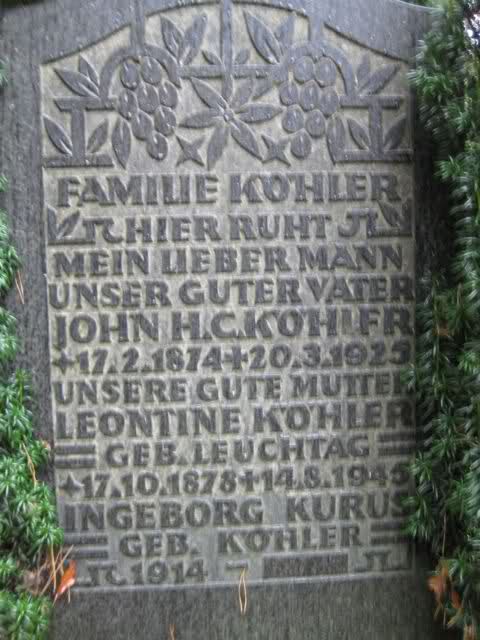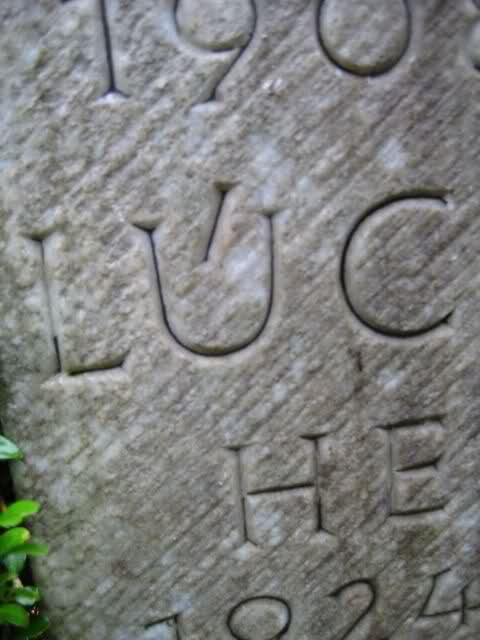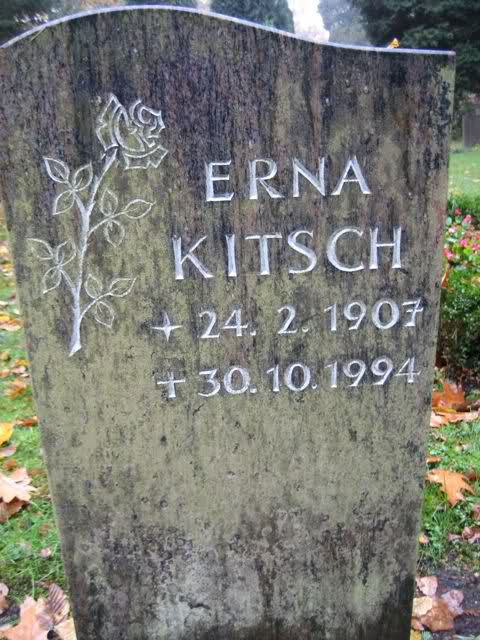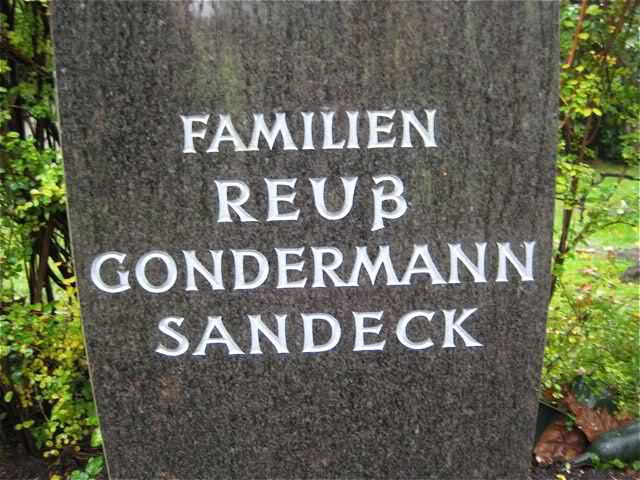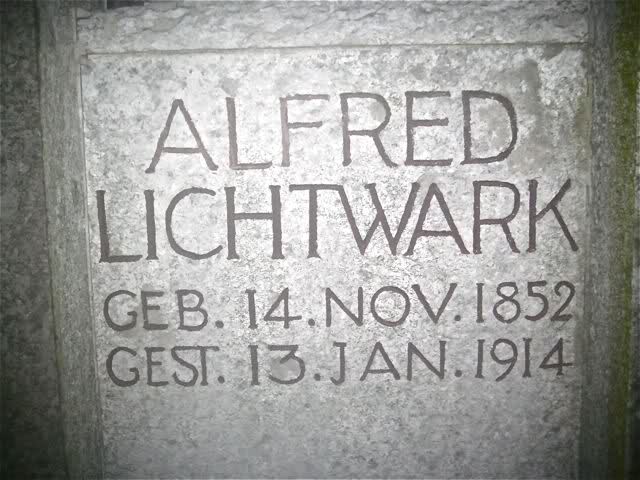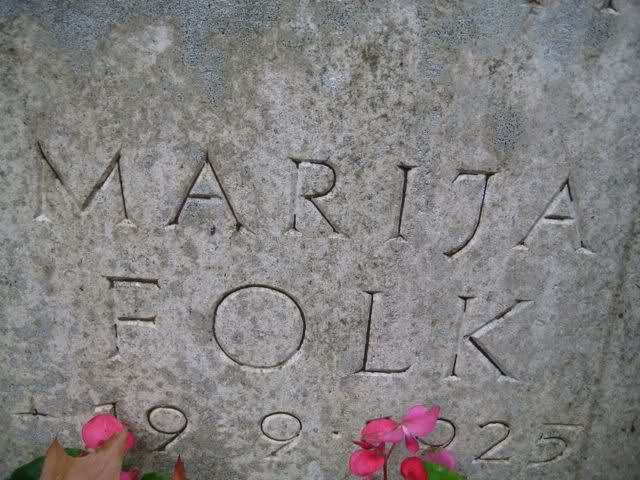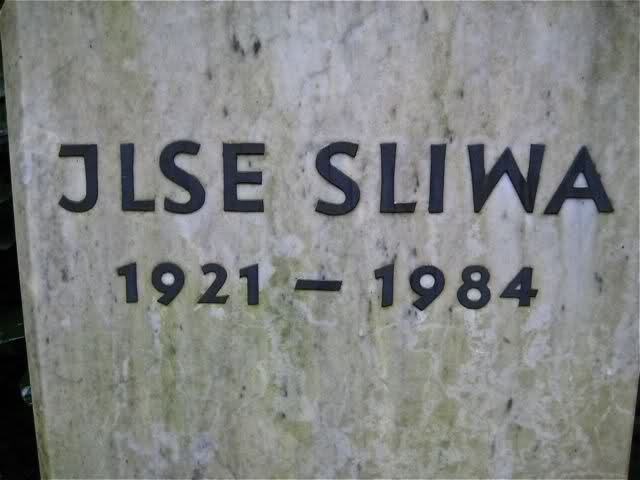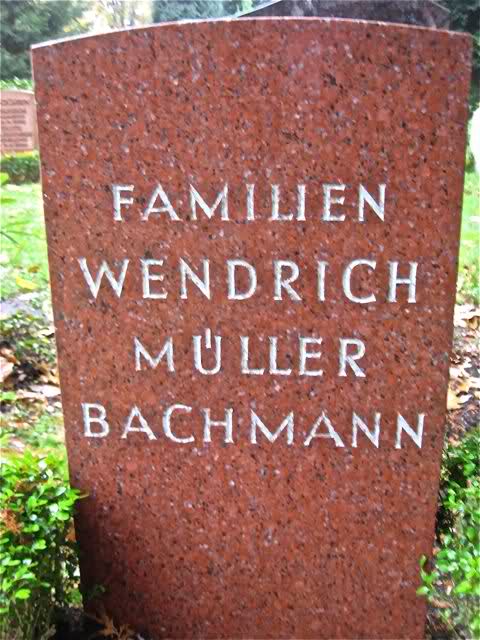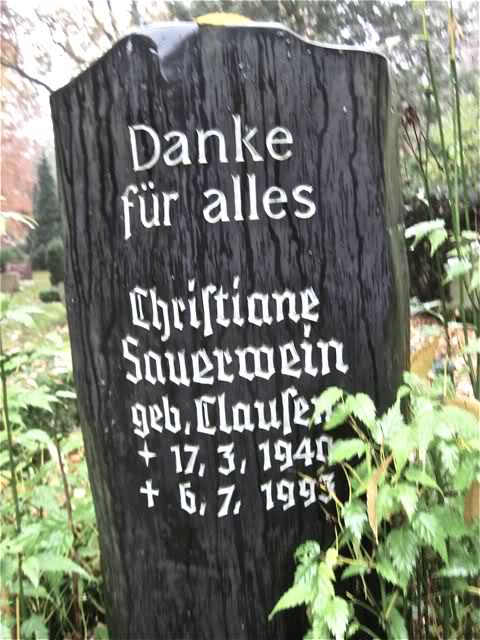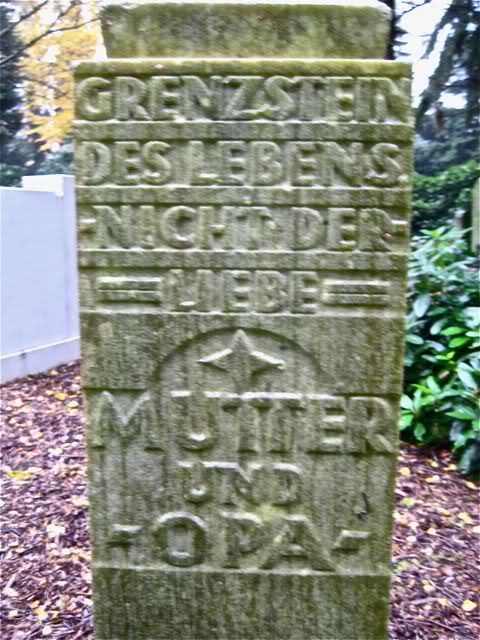
Tombstone-Spotter
Hier kommen die versprochenen Bilder vom Ohlsdorfer Friedhof in Hamburg. :)
Etwas Eszett:
Etwas Blocksatz:
Etwas für den Lang-s-Freund:
Etwas Versalsatz:
Etwas gemischte Schrift:
Etwas ungewöhnlich:
Und zum Abschluss etwas Kitsch:
Du meinst in dem „und meine Seele …“-Ding?
Da ist neben allem grausigen Satz auch noch ein Fehler drin :kopfschüttel:
:scroll ... glotz ... schröckel: Stimmt ... Na, ich glaube fast ich muss demnächst mal einen Herbstspaziergang über den Hauptfriedhof machen :D
Interessant ist übrigens auch, wie viele Varianten es beim Satz der Geburts- und Sterbedaten gibt. Blocksatz, Flattersatz, Bindestrich oder Gedankenstrich, mit Abständen oder ohne. Die Herren Steinmetze sind sich da anscheinend nicht ganz schlüssig … :?
Du meinst in dem „und meine Seele …“-Ding?
Da ist neben allem grausigen Satz auch noch ein Fehler drin :kopfschüttel:
So etwas in der Art habe ich in Ansbach auch schon gesehen, allerdings nicht auf dem Friedhof und nicht in Grotesk, sondern in Fraktur: "lnnenhof" mit kleinem L statt großem i.